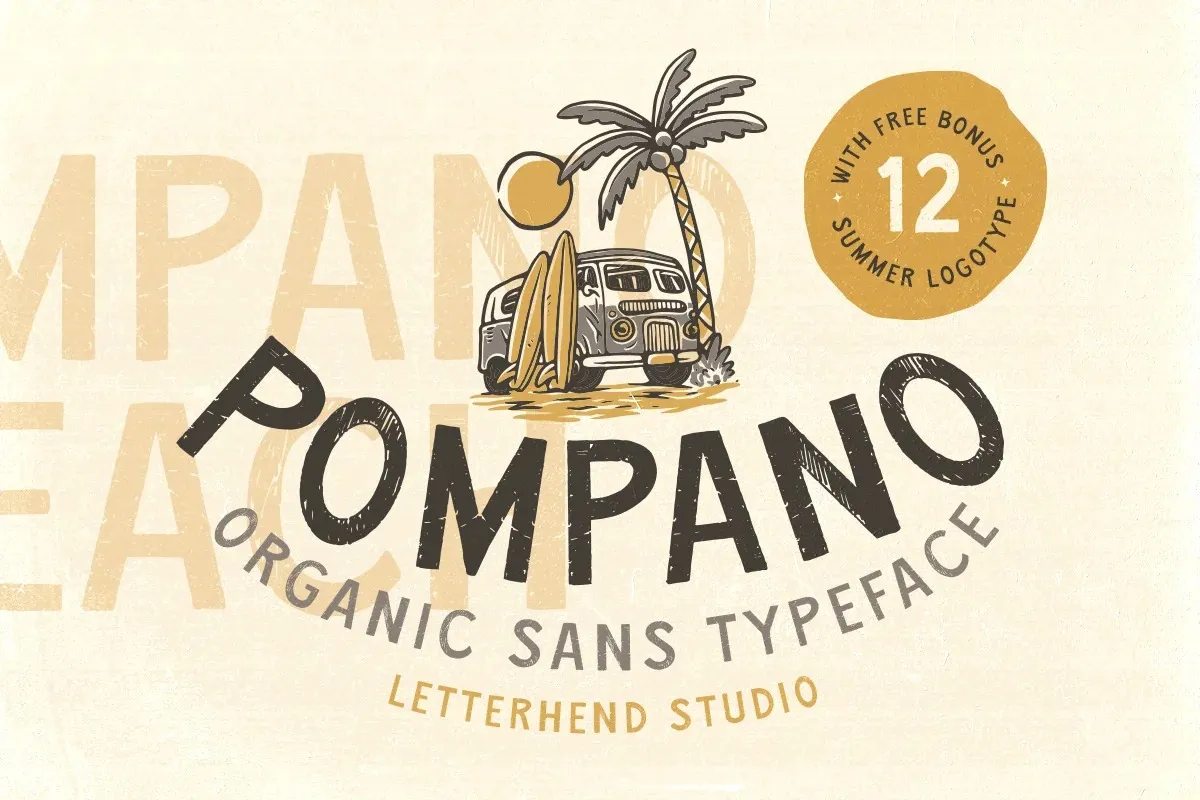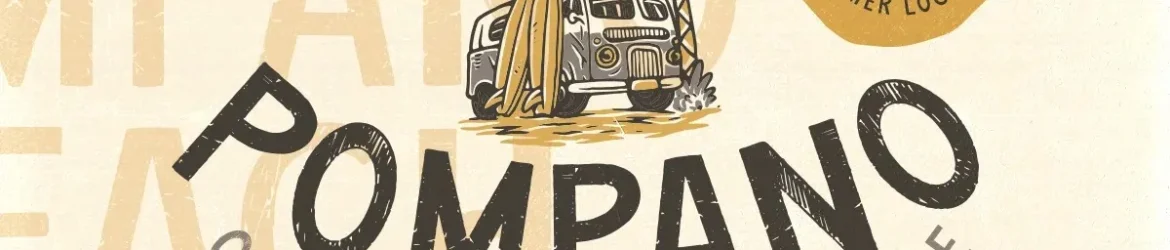
A Pompano Font é uma elegante tipografia de sans serif criada por Letterhend Studio inspirada no estilo visual dos anos 80. Seu uso robusto e único remonta às posters de filmes do então estilos icônicos e distintivos da design gráfico da época. Este tipo de fonte vem com 12 modelos de logotipos, projetado para ser aplicado especialmente em símbolos, além de outras formas formais como convites, rótulos, símbolos corporativos, revistas, livros, cartas de cumprimentos ou casamentos e embalagens. A Pompano Font também se destaca como uma escolha perfeita para anúncios em áreas como moda, maquiagem, papelaria, novelas, selos ou qualquer outro propósito publicitário formal. É uma fonte que traz essência vintage ao design moderno, ideal para quem deseja transpor a atmosfera dos anos 80 de um modo que seja contemporâneo e poderoso ao mesmo tempo.